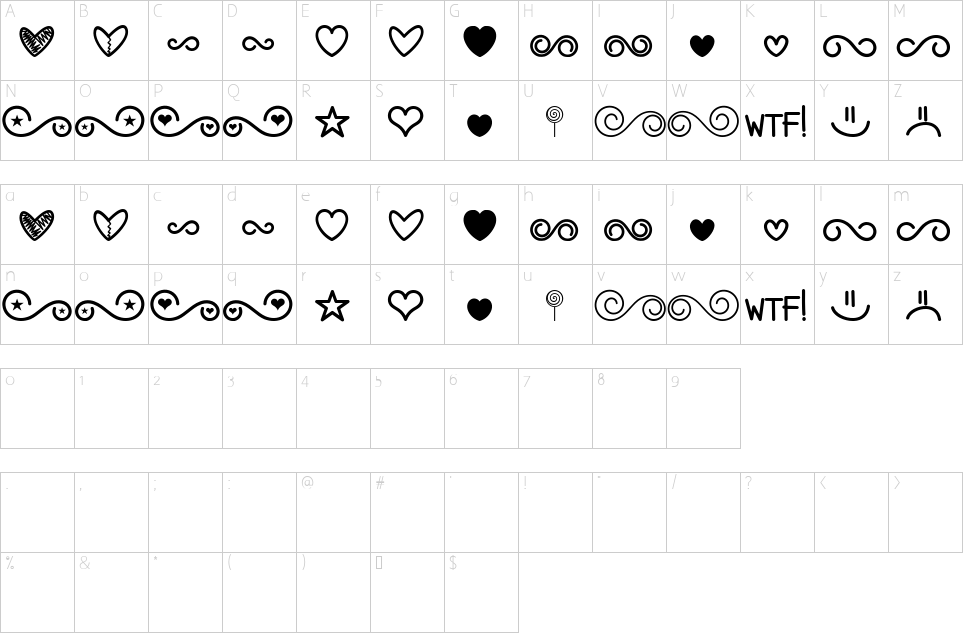
A fonte MF Dings 3 é uma opção moderna e elegante para designers e aficionados pelo design. Desenvolvida pela Misti’s Fonts, esta fonte vem em versões para Windows e Mac, permitindo que você utilize sua beleza em qualquer ambiente de trabalho. Com sua simplicidade e clareza, MF Dings 3 é perfeita para criar designs de texto atraentes e agradáveis ao olho, sejam eles em site, aplicativos ou impressões digitais. Com downloads acima de 50.000 vezes, é evidente que muitos designers estão se rendendo à beleza e ao conforto de usar MF Dings 3. Uma fonte que certamente adicionará um toque de sofisticação a seus projetos. Não perca a chance de adicionar uma fonte de qualidade de alta estética à sua biblioteca.